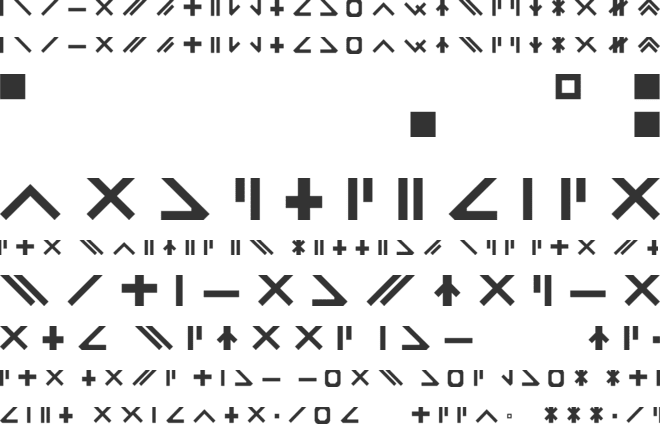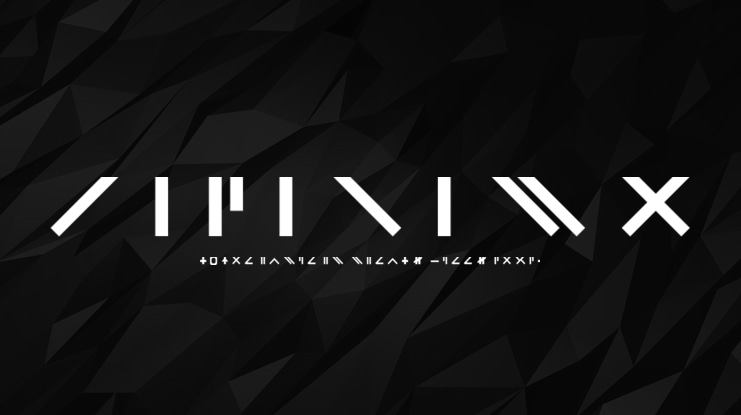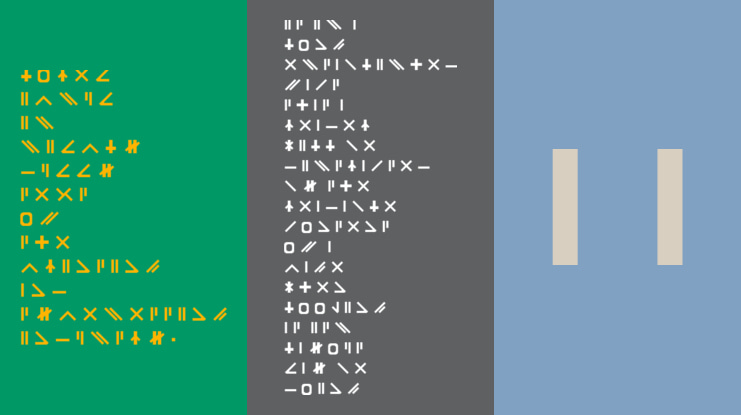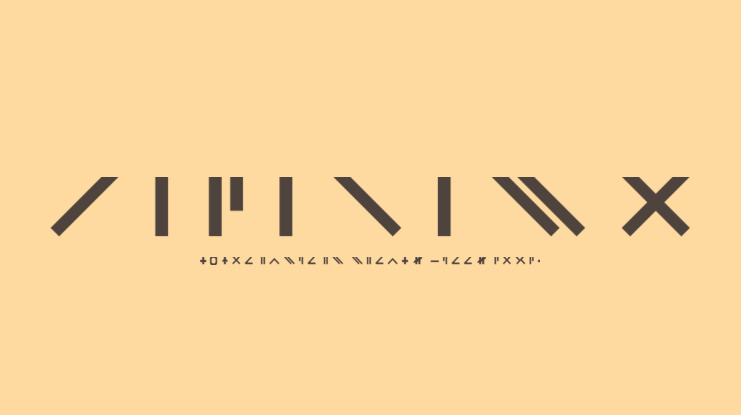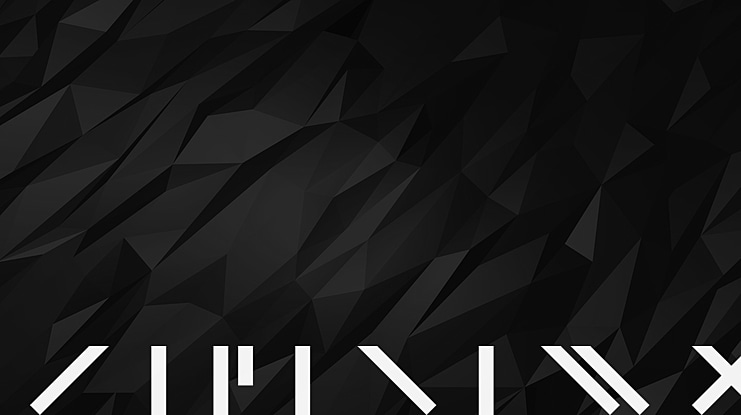
Catabase Font
C'est un langage codé créé par deux amateurs, libre à vous de l'apprendre et de l'utiliser en toute situation possible imaginable. Bien à vous, le directeur interplanétaire et sa secrétaire.